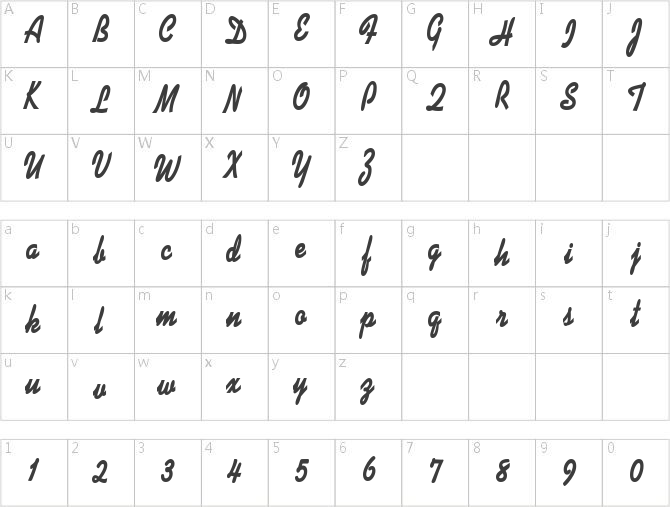
DinerScriptCondensed-Bold 詳情頁(yè)
DinerScriptCondensed-Bold字體字庫(kù)是一款讓人賞心悅目、百看不厭的英文字體,適合各類(lèi)廣告和產(chǎn)品包裝設(shè)計(jì)應(yīng)用,字體大小0.05MB,格式為ttf字體,上傳用戶是董志高,作者/版權(quán)方為未知